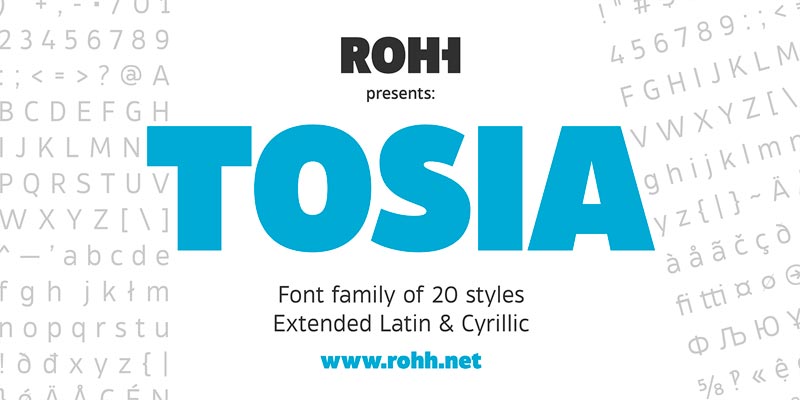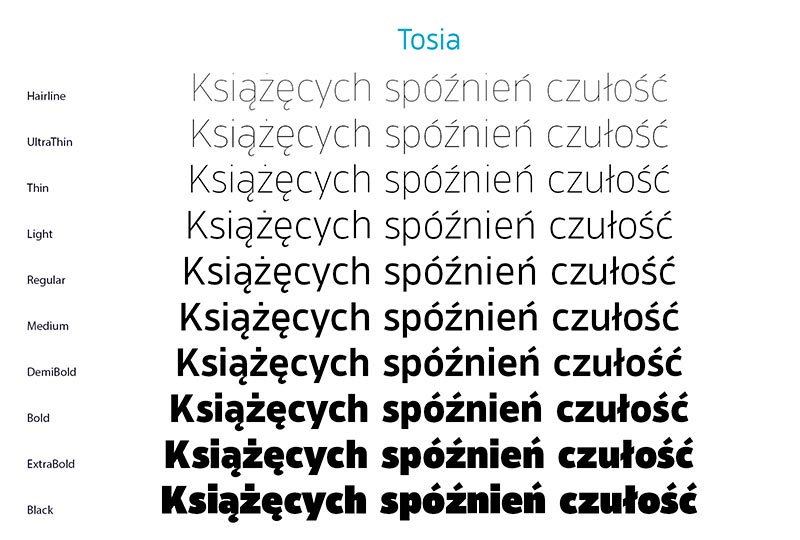
Font Tosia
Zakupiliśmy zestaw fontów Tosia, którego projektantem jest Polak Roch Modrzejewski. Rodzina składa się z 10 odmian grubości i odpowiadających im italików. Tosia to nowoczesny, geometryczny font o czystej formie i wysokiej czytelności.